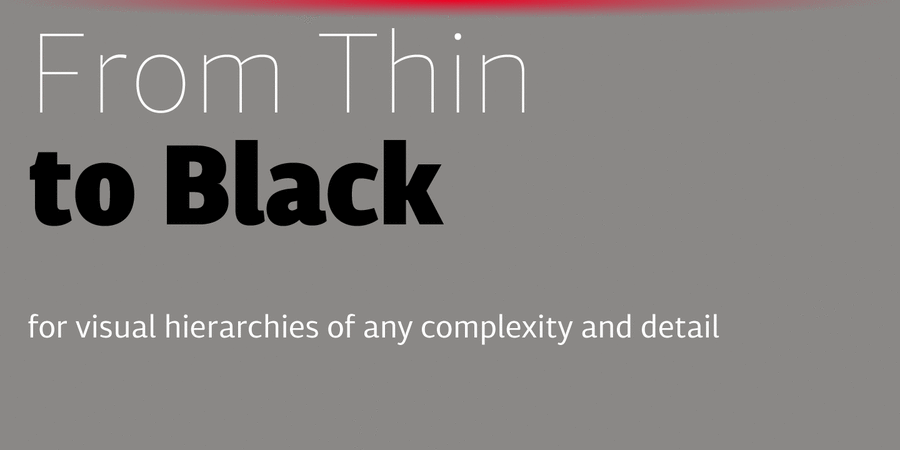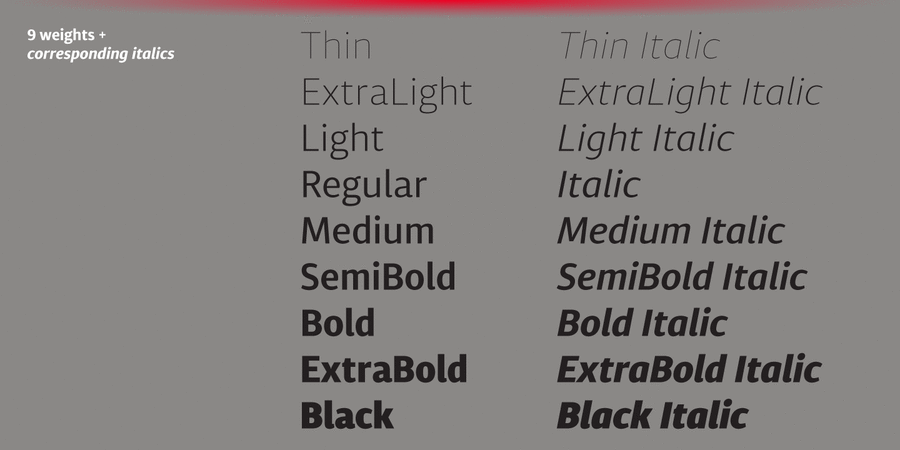
Diaria Sans Pro – це гротескова версія шрифту Diaria Pro. Завдяки широкому набору з 9 насиченостей, курсивних накреслень, розширеної мовної підтримки та різним OpenType-фічам, це шрифтовое сімейство дозволяє створювати візуальну ієрархію у друкованих та мультимедійних виданнях будь-якої складності.
Цей сучасний гротеск розроблений як універсальна читабельна «робоча конячка» для текстів та заголовків. Досить високі рядкові знаки й статичні форми сприяють комфортному читанню, як вузьких газетних колонок, так і сторінок електронних видань.
Шрифт розробив та випустив Андрій Константинов у студії Mint Type в 2016 році.
Асоціації з сімейством шрифтів Diaria Sans ProОсобистість і характер гарнітури:
делікатний, прохолодний, модний, якісний, рівний, спокійний, чистий, сучасний, лаконічний, міський, легкий, свіжий, худий, дорогий, тонкий, невагомий, прозорий, мінімалістичний, інтимний, крихкий, ніжний, повітряний, дротяний, елітний, статичний, врівноважений, космополітичний, ненав'язливий, глобалізований, глобалістічний, довірчий, комфортний, Простий, універсальний, зручний, монотонний, зрозумілий, нейтральний, доступний, помірний, технічний, непомітний, оптимальний, практичний, формальний, діловий, середній, серйозний, логічний, ввічливий, добрий, мирний, мотивуючий, твердий, тісний, стабільний, стійкий, надійний, впевнений, переконливий, сильний, авторитетний, важливий, міцний, значний, солідний, гучний, яскравий, виразний, характерний, помітний, крутий, амбітний, потужний, важкий, масивний
Місто, парфумерія, лосьйон, туалетна вода, косметика, дієта, дизайн, гігієна, шампунь, мода, інновації, чистота, коворкінг, здоров'я, суспільство, бізнес, навігація, транспорт, аеропорт, метро, ліки, інтернет, мобільний зв'язок, логістика, автобус, торгівля, новини, політика, аптека, паливо, енергетика, урбаністика, тренажери, інструмент, банкнота, монета, вантажівка Гарнітура має ознаки стилів: